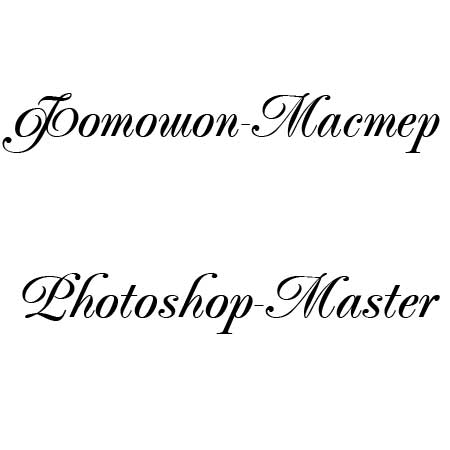
Дополнения Шрифты Татьяна Гапонова 21 февраля 2009 Шрифт - PPLS Красивый рукописный шрифт с поддержкой русского языка. Формат-TTF Размер-41кб Скачать Шрифт - PPLS